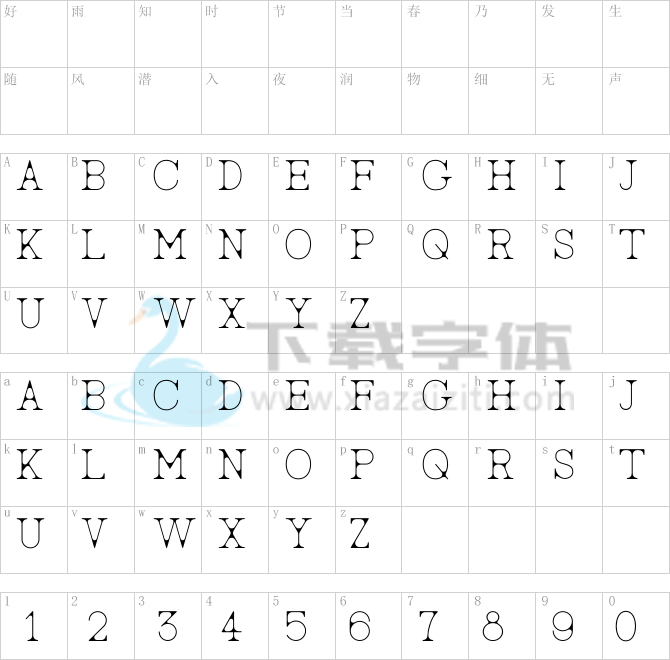
AC Big Serif Two.otf字体下载,这款字体结构工整、笔画清晰,兼顾美观与易读性,适用于标题、正文、海报、包装、LOGO 等多种场景。字形优雅稳定,风格百搭耐看,适配日常排版与创意设计,让文字呈现更舒适、更具质感。AC Big Serif Two.otf字体下载一笔一画,皆是细节,以均衡的比例、流畅的线条打造舒适视觉体验,字形端正大气,风格简约现代。无论是商业设计、品牌宣传还是日常排版,都能轻松驾驭,让文字更有格调与力量。AC Big Serif Two.otf字体下载字体下载。
AC Big Serif Two.otf图片展示